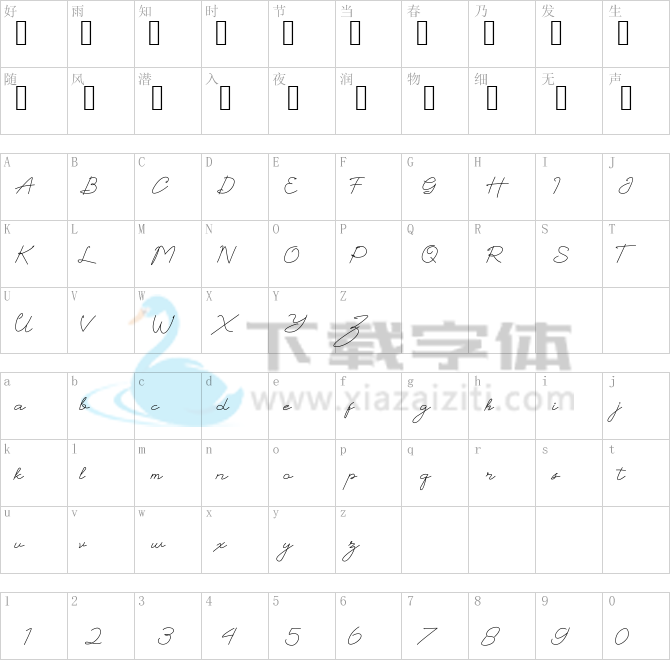
Anthony_Houston.ttf字体下载,这款字体结构工整、笔画清晰,兼顾美观与易读性,适用于标题、正文、海报、包装、LOGO 等多种场景。字形优雅稳定,风格百搭耐看,适配日常排版与创意设计,让文字呈现更舒适、更具质感。Anthony_Houston.ttf字体下载一笔一画,皆是细节,以均衡的比例、流畅的线条打造舒适视觉体验,字形端正大气,风格简约现代。无论是商业设计、品牌宣传还是日常排版,都能轻松驾驭,让文字更有格调与力量。Anthony_Houston.ttf字体下载字体下载。